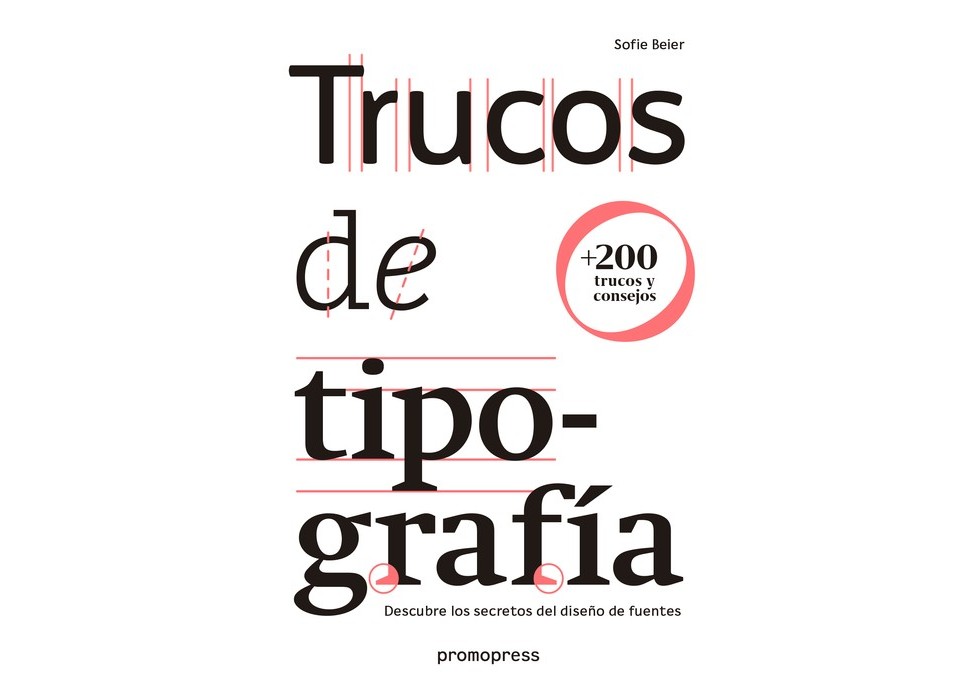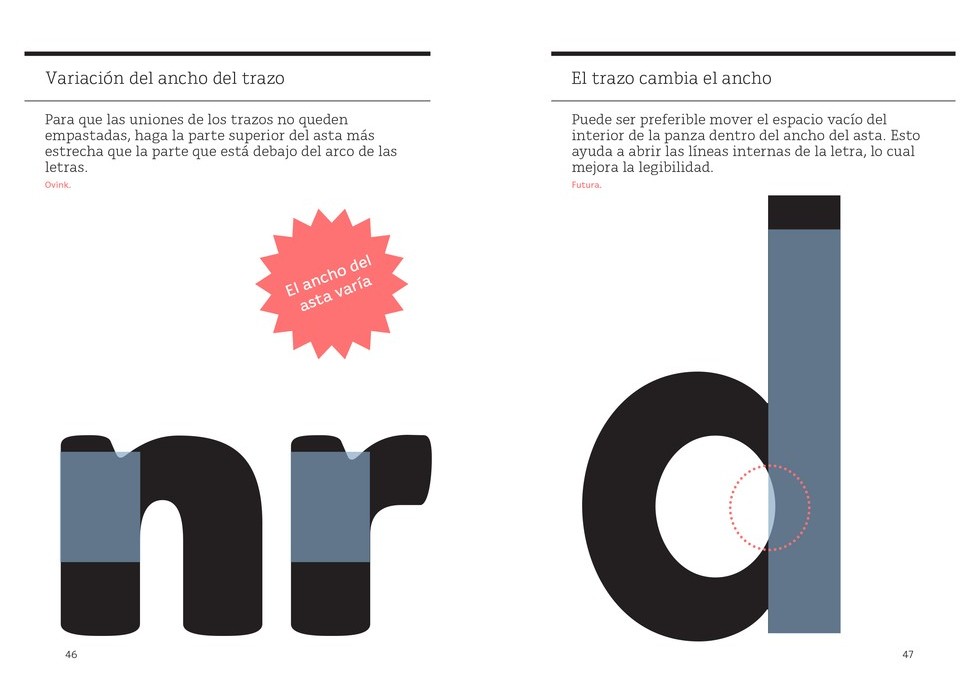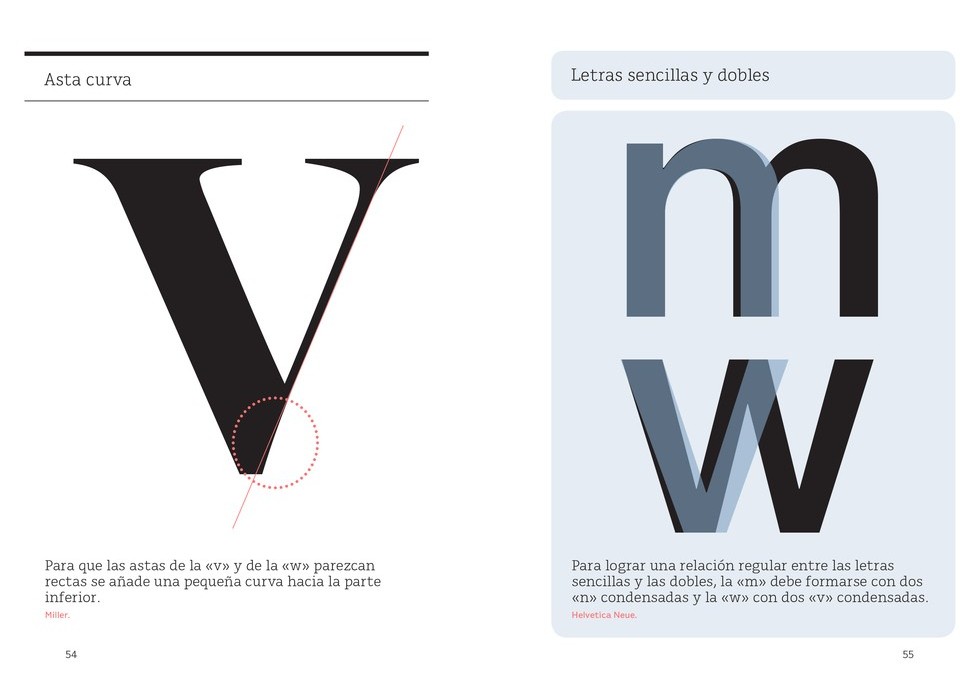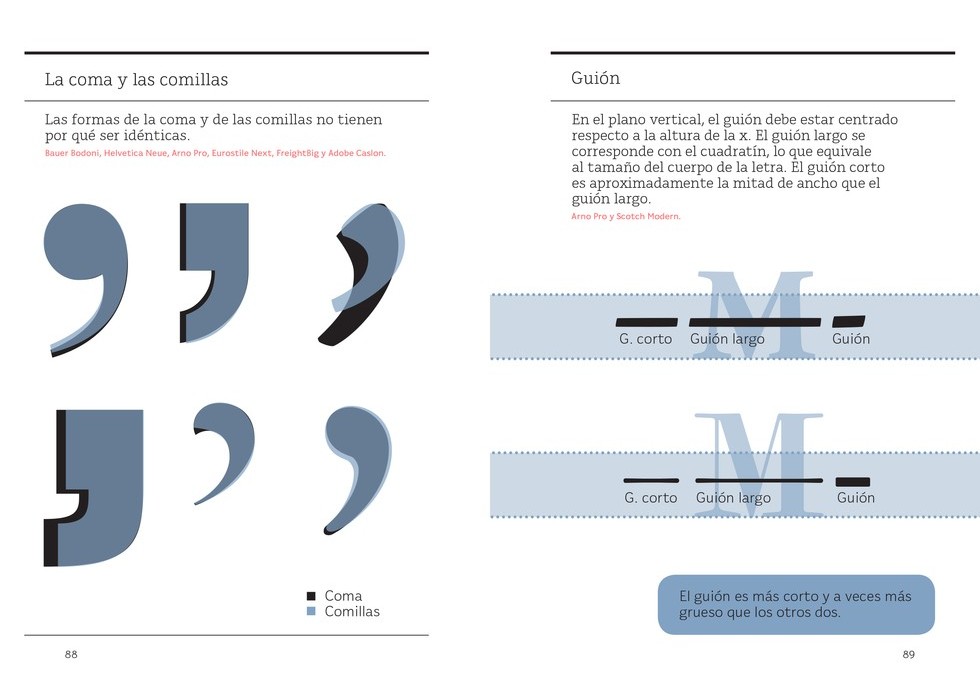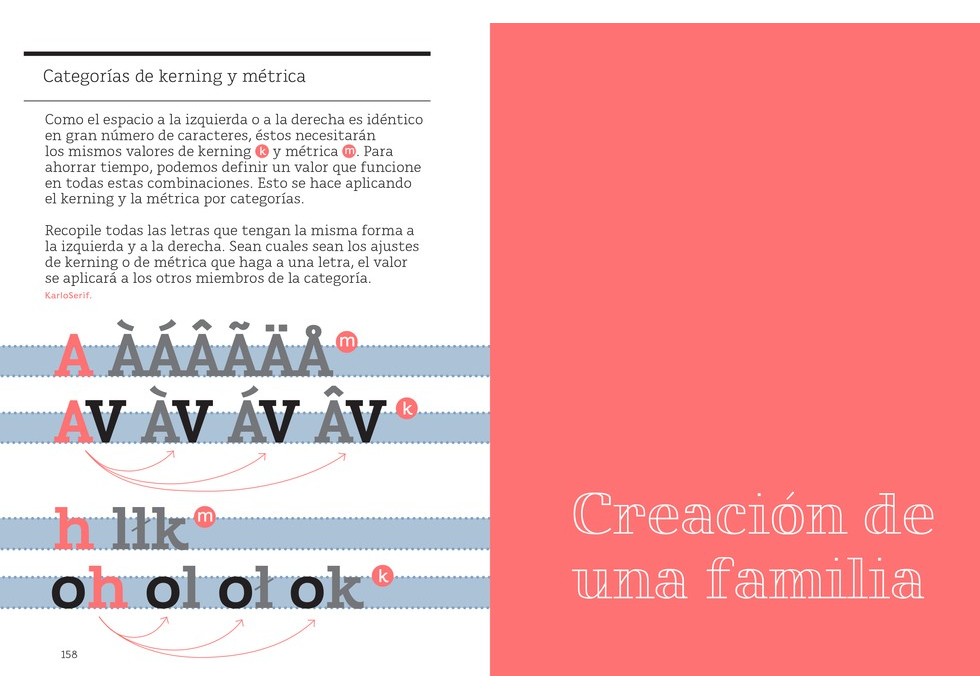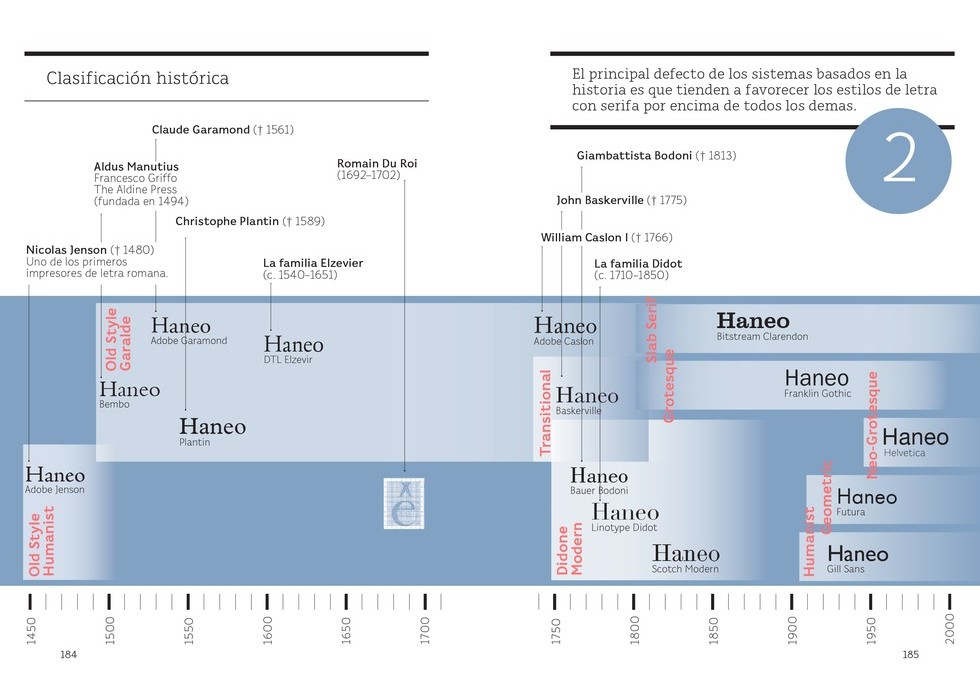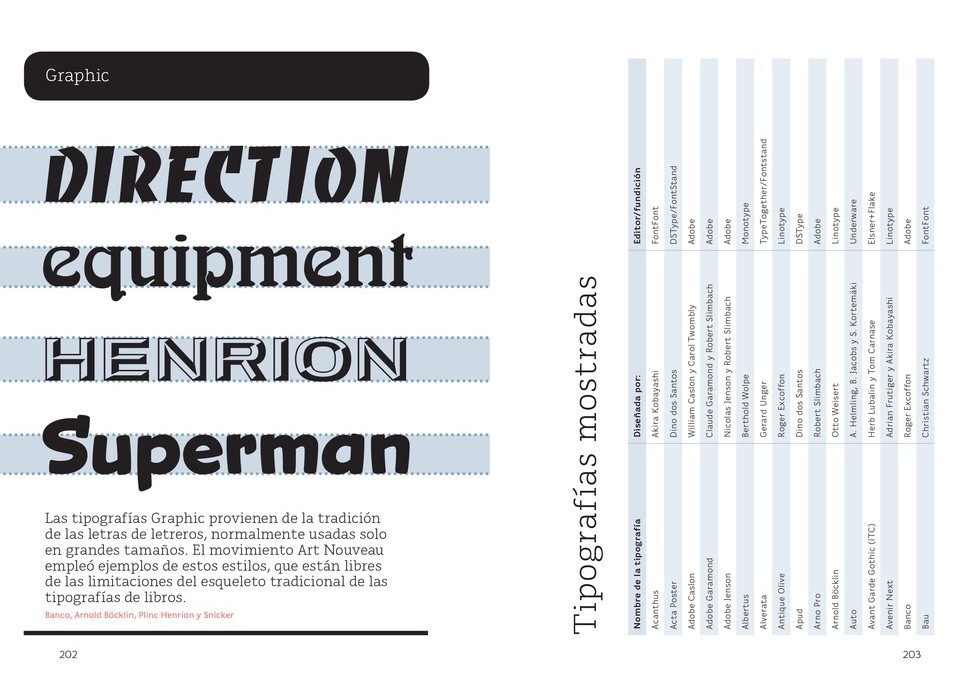
TRUCOS DE TIPGRAFÍA
Descubre los secretos del diseño de fuentes (+200 trucos y consejos)
Sofie Beier
Esta pequeña guía reúne de manera sencilla y muy visual los principios fundamentales del diseño de fuentes. Trucos de tipografía contiene más de 200 trucos y explica detalladamente las reglas, la estructura y las etapas de los procesos de trabajo esenciales para adentrarse en este campo del diseño gráfico. Con ejemplos y propuestas muy claras, el libro muestra cómo observar las formas negativas y positivas y cómo encajar y ajustar las figuras para crear la proporción deseada. Este título aporta una comprensión amplia y profunda de todos los aspectos necesarios para diseñar fuentes con libertad. ¡Podemos olvidarnos de las reglas! Gracias a su clara estructura visual y a su reducido tamaño, Trucos de tipografía es un libro de consulta para usar en cualquier momento, además de un manual de uso que hace muy accesibles las complejas normas de la tipografía. Sofie Baier pone al servicio del estudiante y del profesional su amplia experiencia como profesora de tipografía para que el lector avance y perfeccione la destreza.
Sofie Beier es diseñadora y profesora asociada en la Escuela de Diseño vinculada a la Real Academia Danesa de Bellas Artes, donde dirige el programa de Postgrado de Tipografía y Señalética y doctora por la Real Escuela de Arte de Londres.